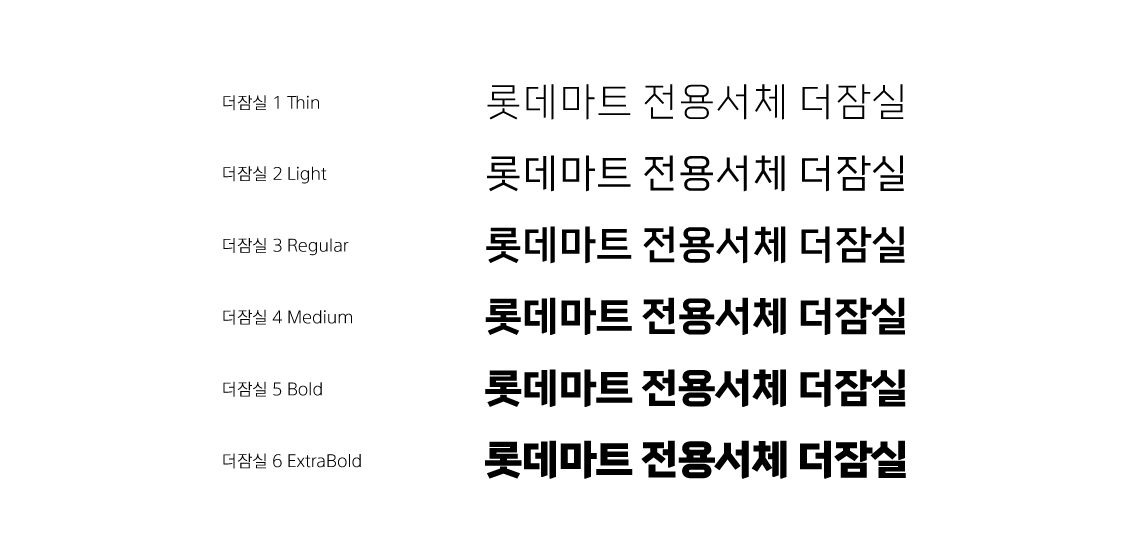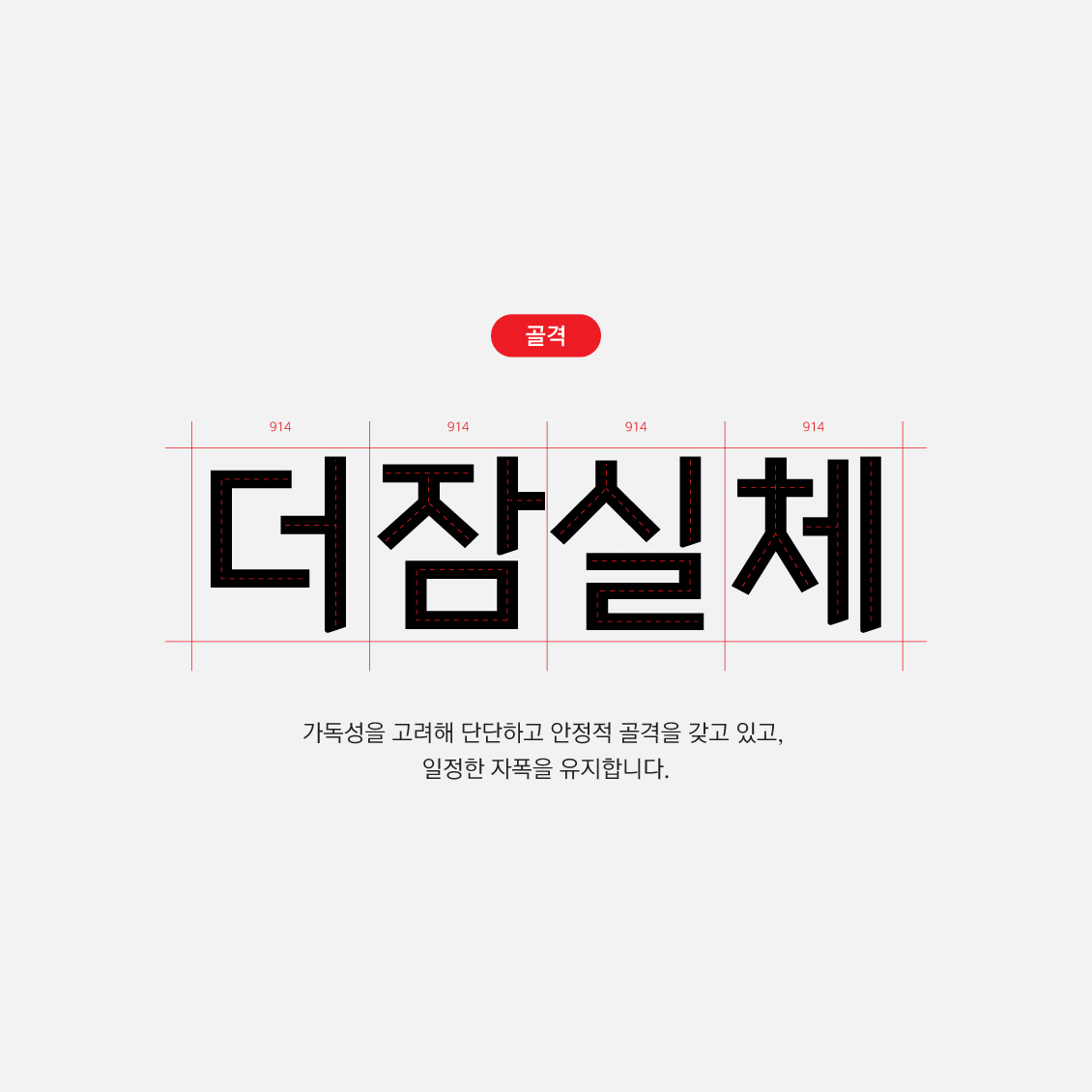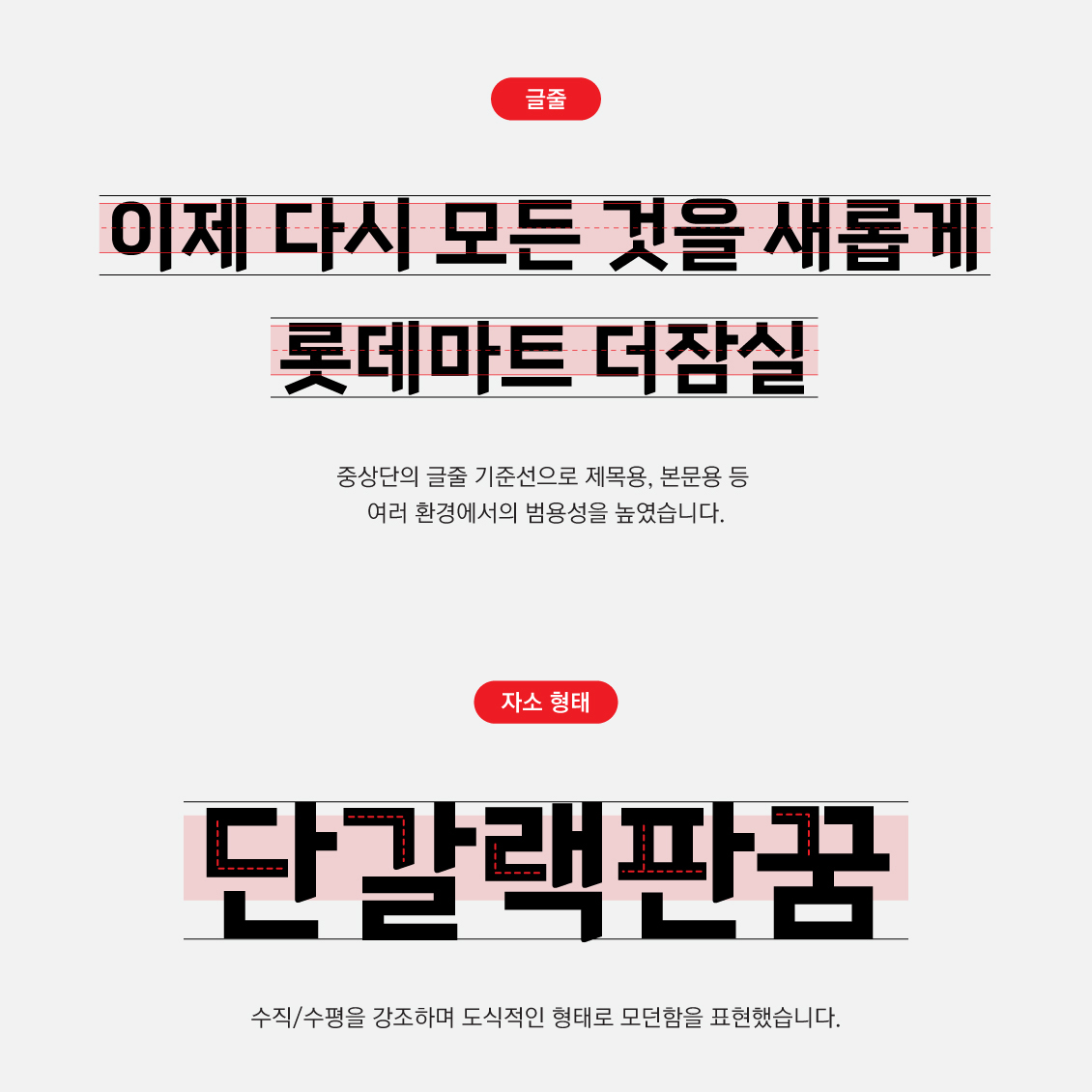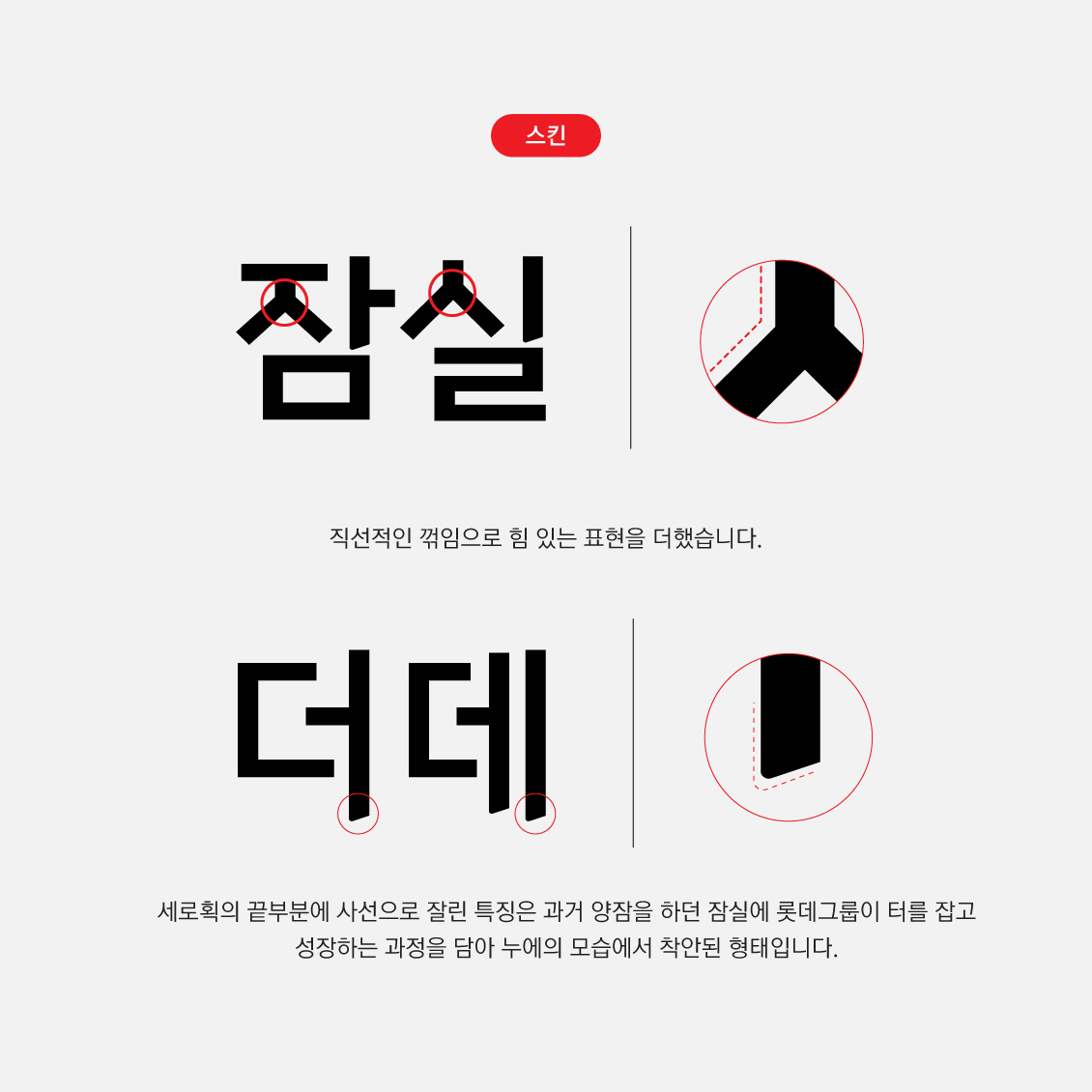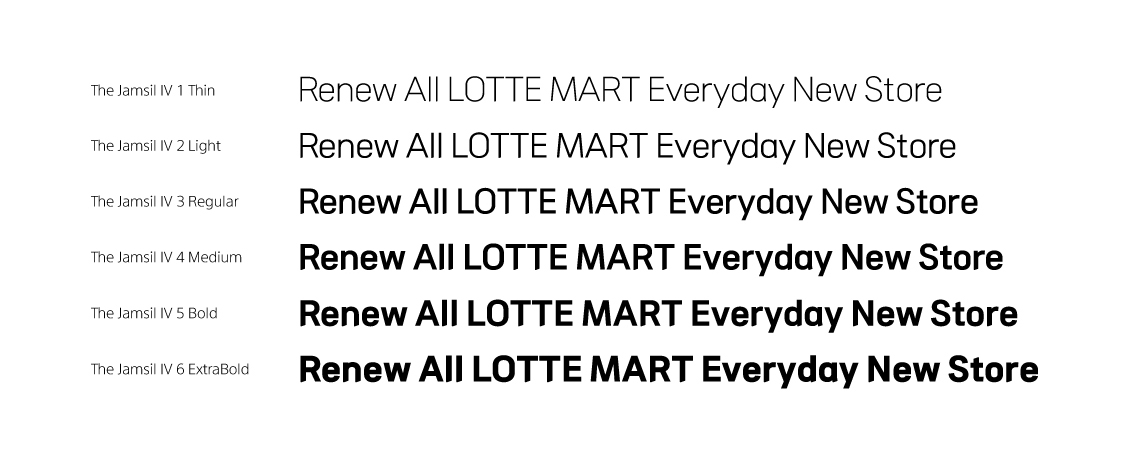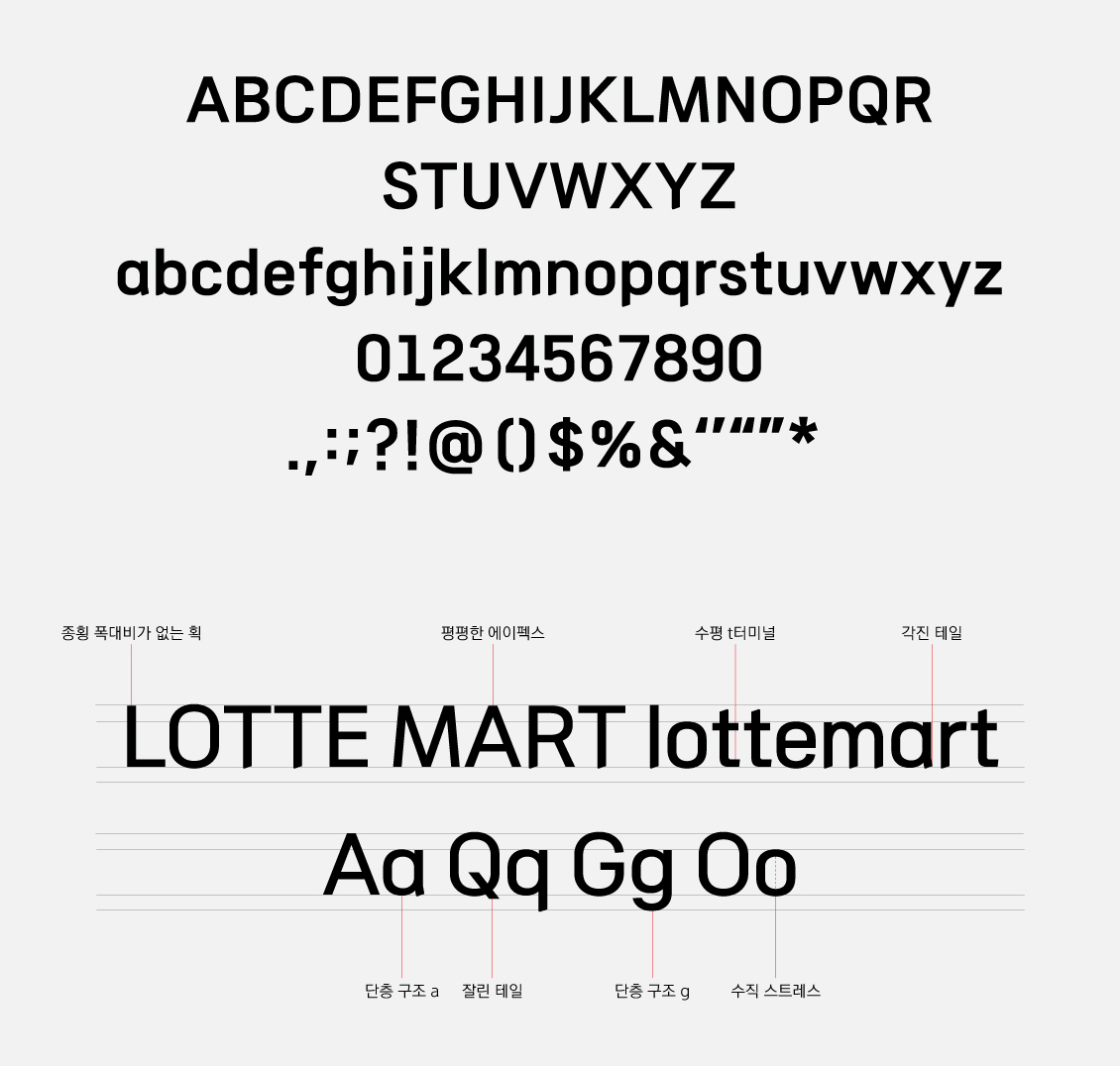
안녕하세요. 오늘은 글로벌 기업 롯데마트의 전용서체로 제작한 「더잠실」을 소개해 드립니다. 기존의 브랜드 이미지를 젊고 새롭게 변화하면서 롯데의 헤리티지 곧 '잠실' 지역의 역사성을 담은 서체를 제작하기 위해 폰트릭스가 제작을 맡아 진행했습니다. 1년 여의 긴 개발 기간을 거쳐 2023년 2월 1일 드디어 출시되었습니다. 많은 분들이 자유롭게 사용할 수 있도록 무료 서체로 배포해 더욱 뜻깊은데요, 한번 자세히 살펴보겠습니다👀
안정적이며 모던한 디자인
더잠실체 한글은 안정적이고 단단한 고딕 모듈로 설계되었습니다. 롯데마트의 특성상 매장 내 홍보물, 각종 인쇄물과 인터넷 홈페이지, 모바일 앱 등 다양한 곳에 활용될 것을 고려하여 가독성과 범용성을 중요하게 생각했습니다. 총 6가지 굵기로 파생되어 제목과 본문에 적절하게 사용할 수 있습니다.
롯데마트의 새로운 비전인 'Everyday New Store'에 걸맞은 젊고 신선한 이미지를 주기 위해 적은 획대비(굵기의 비례)와 수직/수평적인 획, 대각선 등의 도식적인 형태를 넣어 깔끔하고 모던한 디자인으로 제작했습니다.
큰 글씨나 작은 글씨 상관없이 잘 보이고 읽히도록 가독성을 고려해 디자인했습니다.
잠실의 역사성을 담다
더잠실체는 특별한 스토리가 담겨있습니다. 과거 양잠을 장려하던 지역인 잠실은 '누에를 치는 방'이라는 뜻을 갖고 있는데요. 롯데그룹이 잠실에 터를 잡고 대한민국을 대표하는 기업으로 성장한 과정을 담아 누에의 일생을 서체 디자인에 녹여냈습니다.
누에고치의 둥글고 길쭉한 형상을 닮은 'ㅇ'꼴, 명주실이 뽑아져 나오는 생동감을 표현한 힘 있는 각, 누에가 머리를 드는 모습을 현대적으로 해석한 획의 끝부분 등 디자인적 특징을 확인할 수 있습니다.
이처럼 직선과 곡선이 만나는 적절한 디자인적 요소들이 기본기가 탄탄한 서체의 골격과 밸런스를 이루어 최상의 완성도를 가질 수 있도록 노력했습니다.
꾸밈이 적고 베이직한 형태일수록 사용성은 높아지고 생명력이 긴 서체가 된다.
박용락 총괄 디자이너
글로벌한 폰트 개발
해외 사업을 펼치고 있는 롯데마트의 영향력을 고려해 다른 언어권 서체 개발까지 진행했습니다. 더잠실체의 디자인적 특징을 그대로 반영한 라틴(영문), 베트남 및 인도네시아어 개발로 해외에서도 한글의 아름다움을 느낄 수 있도록 하는 것을 목표로 했습니다.
The Jamsil Ⅳ는 한글과 혼용 시 자연스럽게 어우러지며 활용성을 고려해 한글과 동일하게 6가지 웨이트로 제작했습니다.
두께 대비가 없는 획, 각지고 잘린 테일, 지오메트릭한 디자인 등 한글의 형태적 특징을 유지하며 라틴 문자와 숫자, 문장부호 디자인을 진행했습니다.
또한 사용 환경을 고려해 Condensed 버전의 제목용 서체 2종을 추가로 제작했습니다. 타이틀에 쓰기 좋은 ExtraBold와 Black 두 가지 굵기로 기존 더잠실체의 약 90% 평의 구조를 띄도록 디자인하여 큰 글씨에 활용할 수 있습니다.
생활 속에서 발견하는 더잠실체
이미 롯데마트의 여러 콘텐츠에 더잠실체가 활용되고 있는데요. 온라인과 오프라인 어느 곳에서 사용해도 잘 어우러지며 기업의 아이덴티티를 뿜어내 전용서체로서 톡톡한 역할을 하고 있습니다.
롯데마트 매장에 간다면 서체가 사용된 곳들을 찾아보는 재미도 쏠쏠할 것 같습니다🙂 고객과 만나는 모든 접점의 글씨에 적용된다고 하니 생활 속에서 자주 만나볼 수 있기를 바랍니다.
많은 기업들이 전용서체를 개발하고 무료로 배포하고 있지만 이는 작은 결정이 아닙니다. 서체 제작에는 수많은 사람들의 노고와 시간, 자원이 들어가기 때문입니다. 더잠실체는 롯데마트와 폰트릭스의, 특히 젊은 신입 디자이너들이 머리를 맞대고 트렌드와 범용성 등의 기준에 부합하는 서체를 제작하기 위해 1년 여의 기간 동안 여러 번의 토론과 협의를 거쳐 개발했습니다.